字体是企业形象识别系统基本要素之一,应用广泛参与标志联系在一起,具有明确的说明性,可以将设计的理念最直观的传达给看客,与视觉、听觉同步传递信息,强化企业形象与品牌诉求力。今天要给大家推荐的这个种类字体,跟普通字体相比更具特色,有着极强的视觉冲击力。咱们一起来看看下面图片字体了解一下吧~
汉标空心手体:通常字形中的点、撇、捺、钩、提等笔画各具面目,笔画末端用了手势图形元素来构建,把这些笔画做成了空心,概括为飘逸的手体指向,并且使左右舒展的笔画尽量对称,最大限度地简化笔画箭造型。
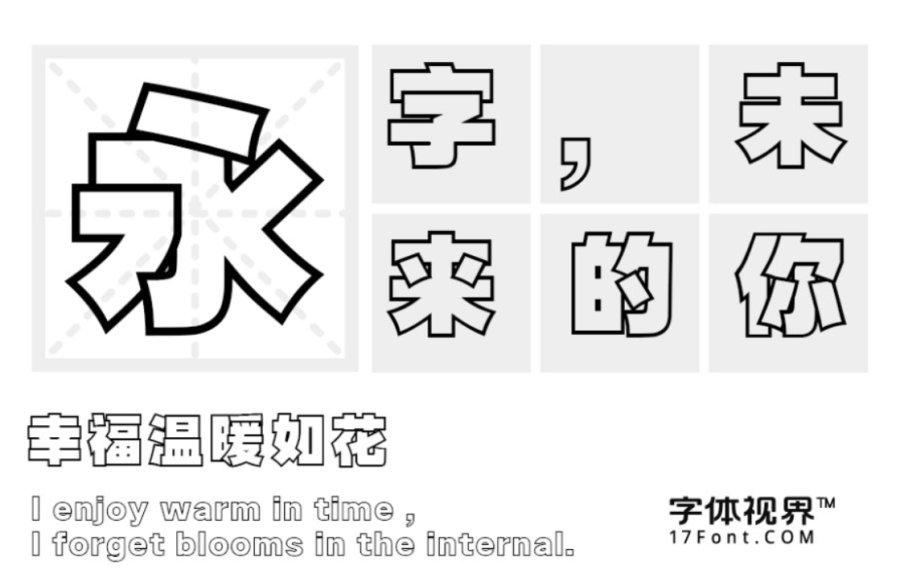
三极空叠体:三极空叠体用笔画叠加的形式展现字体风格,字形清新,结构严谨,方正得体,布白均匀,重心一致。适用于各类便携式屏幕的系统嵌入字体,以及传统印刷媒介的标题与正文排版。在品牌形象设计中作为logo设计性文字视觉效果更佳。
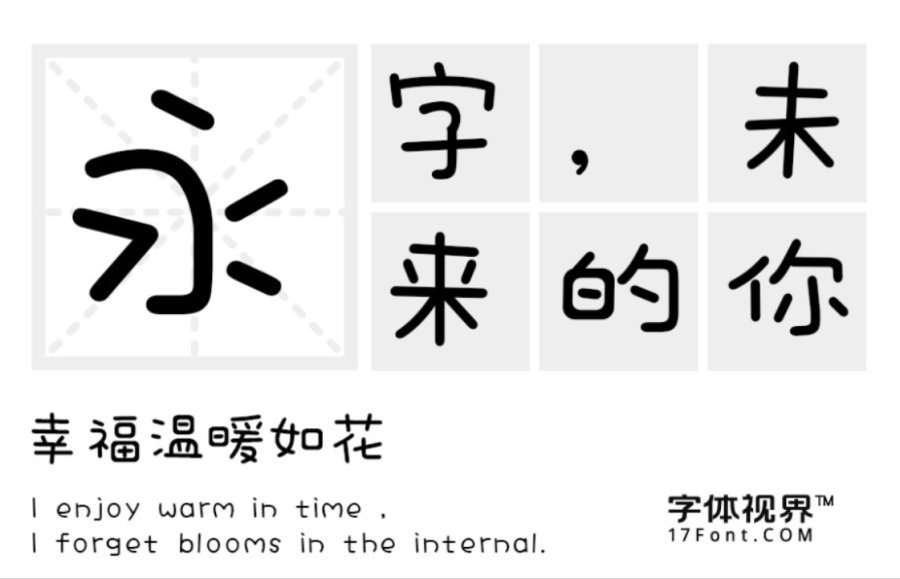
三极真喵简体:三极真喵简体用儿童写字的简拙,笔画轻松、简洁,童趣随性。字形饱满圆润,轮廓略显臃肥,整体个性明快可爱。适用于少儿类读物、书刊、品牌广告、包装设计以及社交网络个性化用字。